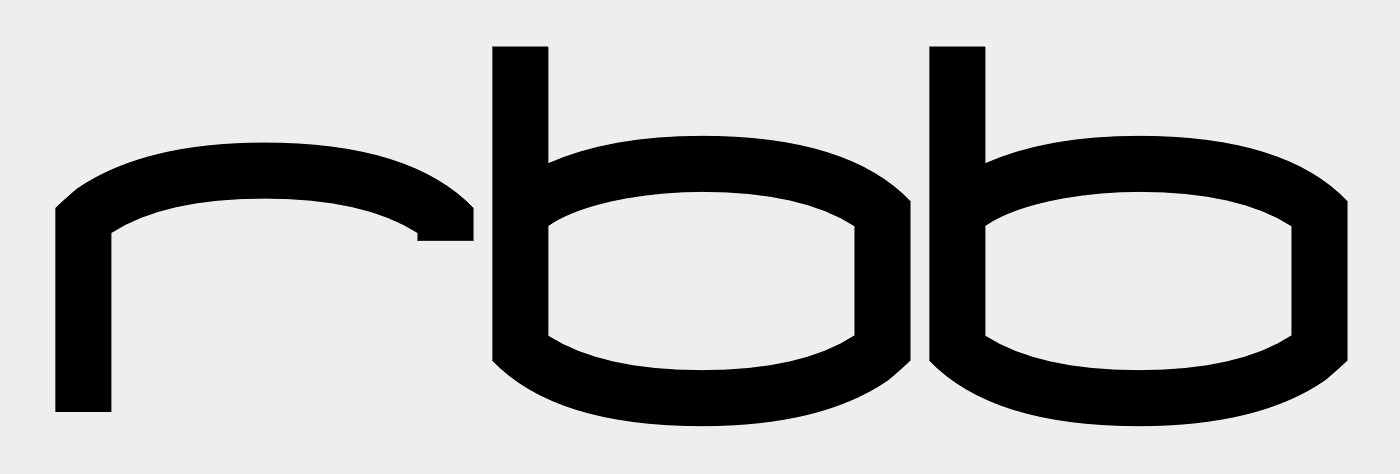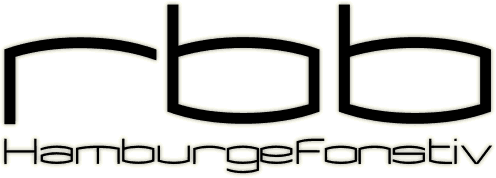
rbb Dachmarke (Rundfunk Berlin-Brandenburg)
Ohne das jetzt belegen zu können, würde ich mal ganz stark davon ausgehen, dass die beiden Buchstabenformen extra für das Logo gezeichnet worden sind.
Danke für die Rückinfo. Ich kann mich erinnern, dass es eine Schriftart dazu gibt. Leider ist mir entfallen, wie diese heißt. Ja, man mag glauben, dass es extra als Logo gestaltet wurde.
Eine ähnliche, kostenlose Schriftart wäre die Kameleon (Hier – ganz oben). Es gibt drei Schnitte, die dargestellte, eine noch dünnere Version und ein „Upper“ genannte Variante bei denen die kleinen Selbst- und Umlaute, etwas hochgesetzt und unterstrichen sind.